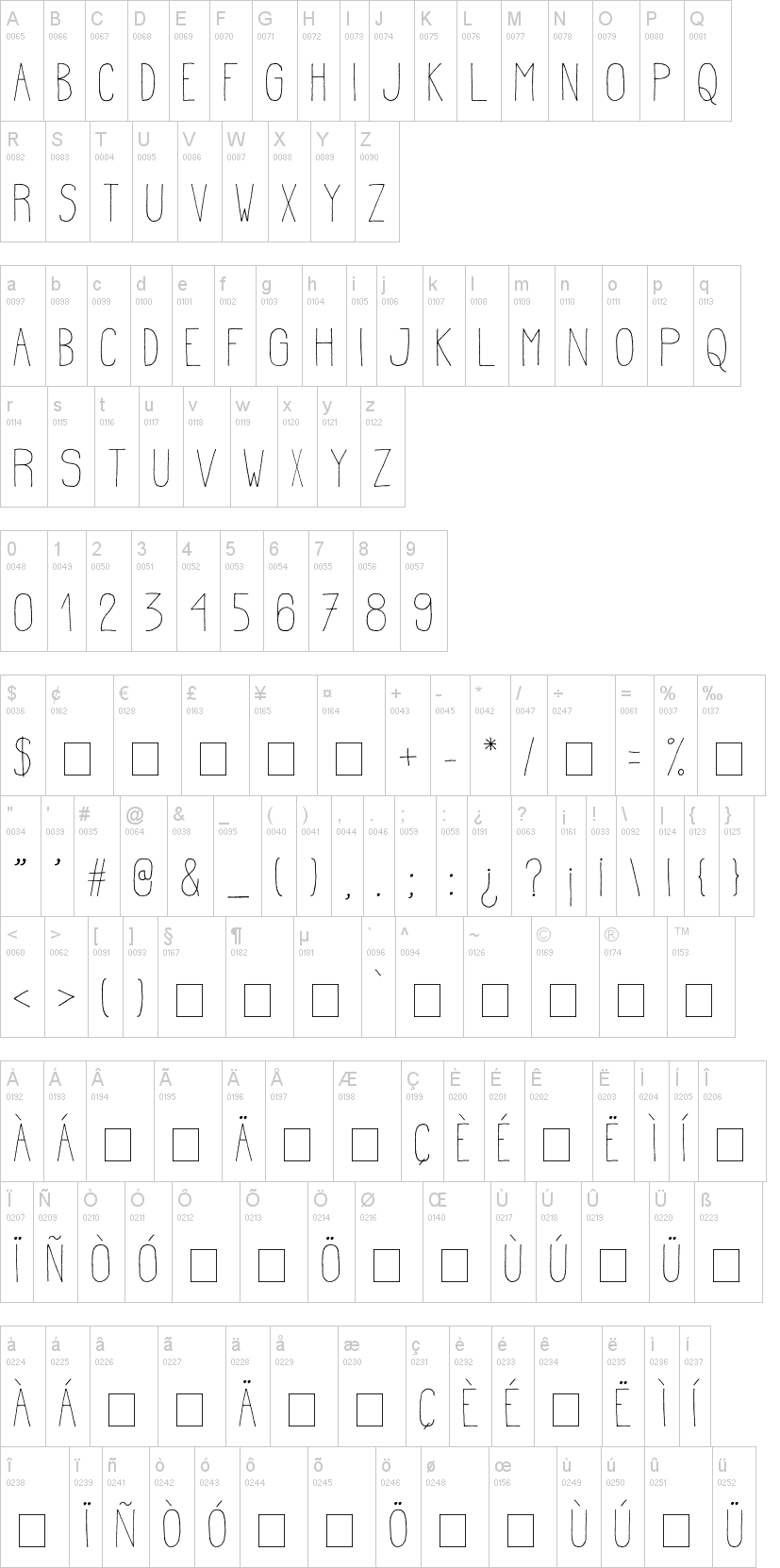
Note of the authorFuente creada para el fanzine "Manual práctico para eliminar la publicidad de tu vida" (http://www.molestar.org/2013/08/09/manual-practico-para-eliminar-la-publicidad-de-tu-vida/)